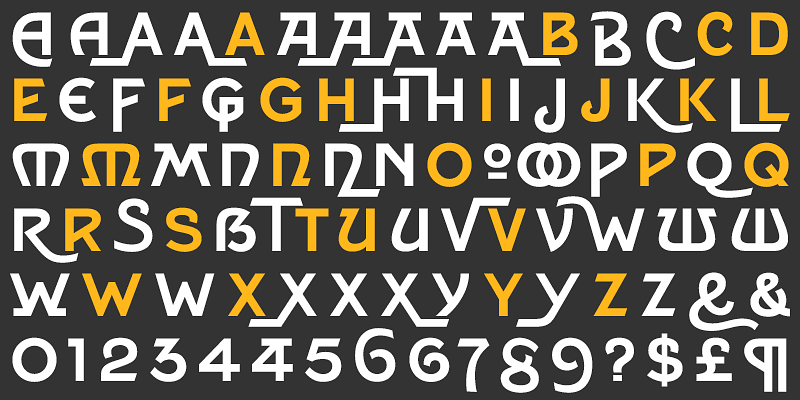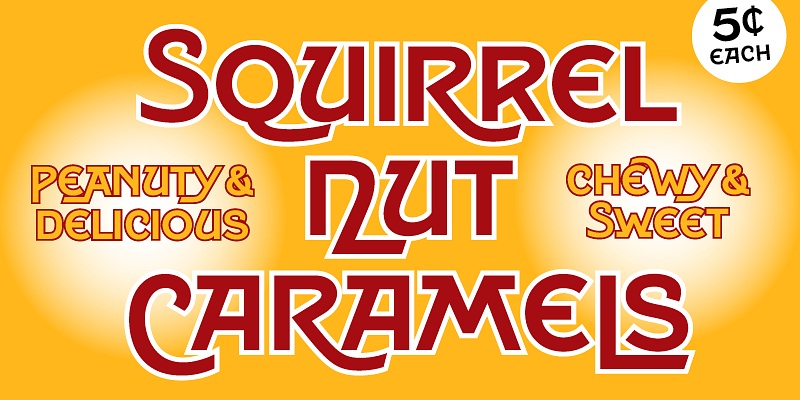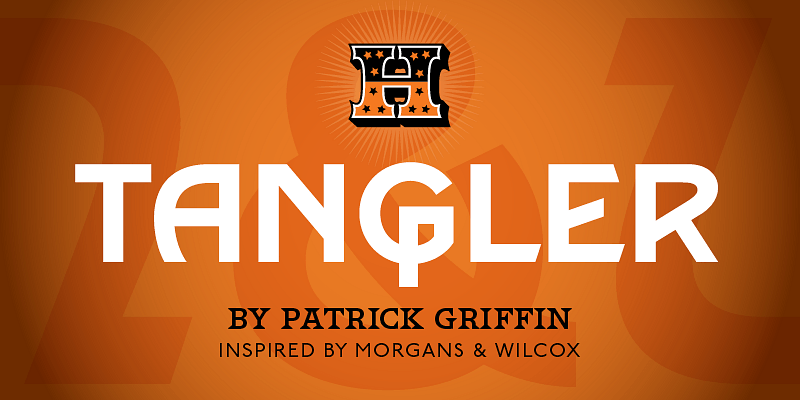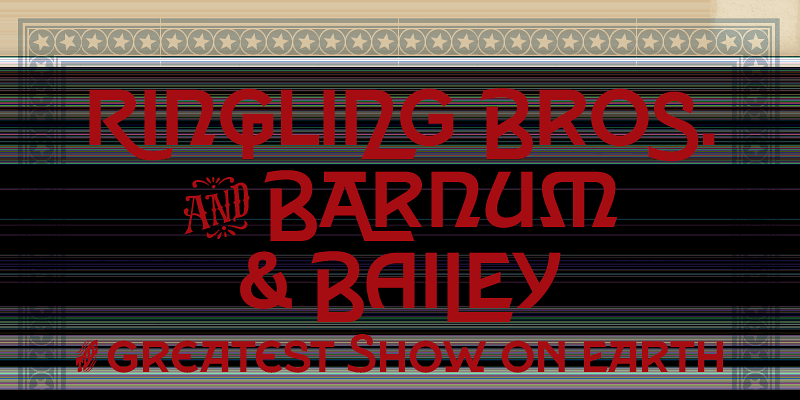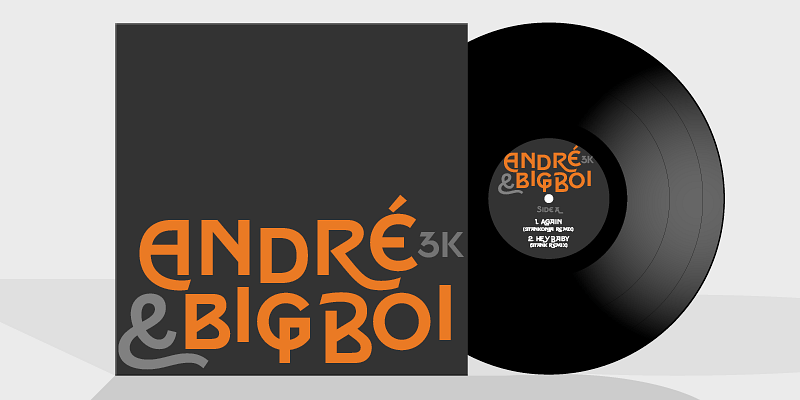
Hamilton Wood Type Collection, fundada en 2012, es una empresa conjunta donde colaboran P22 Type Foundry y el Hamilton Wood Type & Printing Museum. El objetivo principal se basaba en salvaguardar la primera época de la tipografía y hacer que los diseños clásicos de letras tipo madera estuvieran disponibles como fuentes digitales para el público actual. En esta colección histórica retrotrae al serif, se reinterpreta el sans, se usan adornos decorativos, se reclaman alfabetos y se plasman diseños cromáticos originales, adaptándose increíblemente y siendo muy versátil en cualquier idea de diseño imaginativa.